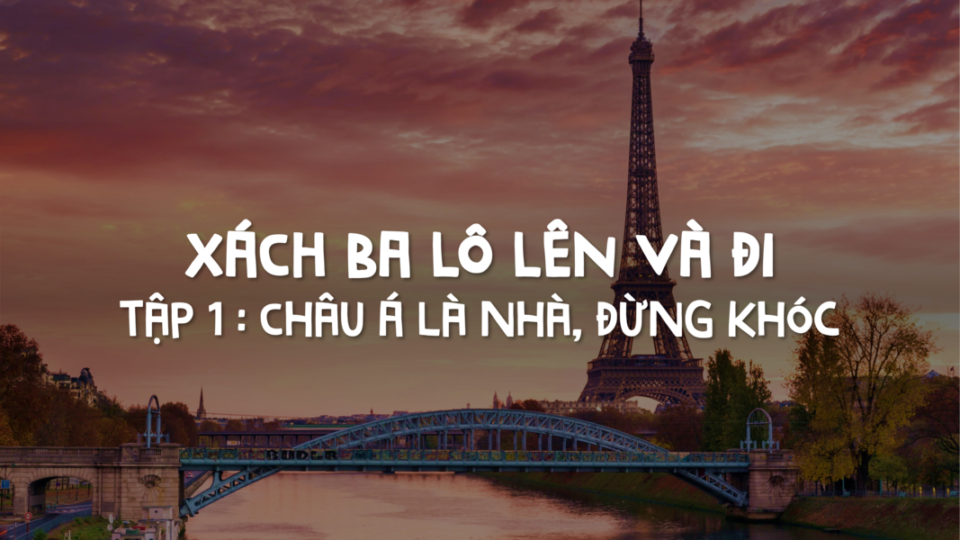
Trong thế giới đồ họa hiện đại, việc lựa chọn Font Miễn Phí chất lượng đóng vai trò then chốt giúp tác phẩm trở nên ấn tượng. Font Việt Hoá SVN-Marujo là một ví dụ điển hình về sự kết hợp giữa nét vẽ tay mộc mạc và cấu trúc hiện đại. Được phát triển dựa trên cảm hứng từ nghệ thuật thủ công, bộ font này mang đến cảm giác gần gũi nhưng không kém phần chuyên nghiệp. Đây là lựa chọn hoàn hảo cho các bạn học sinh muốn làm báo tường điện tử hoặc giáo viên thiết kế bài giảng sinh động.
Đặc điểm nổi bật của Font Việt Hoá SVN-Marujo
Thiết kế thủ công tinh tế
Font Việt Hoá SVN-Marujo sở hữu những đường nét uốn lượn tự nhiên, tạo nên một phong cách chữ viết tay đầy cá tính. Các ký tự được điều chỉnh khoảng cách hợp lý, giúp văn bản dễ đọc ngay cả khi sử dụng ở kích thước nhỏ. Điểm mạnh của bộ chữ này là sự linh hoạt, phù hợp cho cả tiêu đề lẫn các đoạn văn bản ngắn mang tính trang trí.
Tương thích hoàn hảo với tiếng Việt
Phiên bản này đã được tối ưu hóa toàn bộ hệ thống dấu tiếng Việt, loại bỏ hoàn toàn lỗi hiển thị thường gặp. Người dùng có thể yên tâm sử dụng Font Việt Hoá SVN-Marujo trên các phần mềm phổ biến như Photoshop, Canva hay Microsoft Office mà không lo bị mất nét hay sai dấu. Điều này cực kỳ hữu ích cho các dự án thiết kế thiệp mời, bìa sách hoặc poster sự kiện trường học.
Ứng dụng Font Việt Hoá SVN-Marujo trong thực tế
Bộ font này đặc biệt được ưa chuộng trong các dự án đòi hỏi sự sáng tạo và cảm xúc. Bạn có thể sử dụng nó để trang trí ảnh kỷ yếu, làm phụ đề video hoặc thiết kế logo thương hiệu cá nhân. Với vẻ ngoài thân thiện, nó giúp truyền tải thông điệp một cách nhẹ nhàng và sâu sắc đến người xem.